Pubblicato: 2023-05-22Hai difficoltà a trovare il carattere della firma perfetto che corrisponda alla tua estetica e al tuo stile? Non guardare oltre il nostro elenco completo dei migliori font per firme (gratuiti ea pagamento).
In questo articolo, abbiamo curato un elenco dei migliori caratteri di firma per tutte le tue esigenze di progettazione. Con opzioni che vanno dal gratuito al premium, avrai accesso a una varietà di caratteri di alta qualità a portata di mano.
Sapevi che l'utilizzo di un carattere distintivo può aggiungere un tocco personale ai tuoi progetti e aumentare il riconoscimento del marchio fino all'80%? È vero: l'incorporazione di caratteri distintivi nel tuo lavoro può avere un impatto significativo sulla qualità complessiva del tuo design.
Preparati a scoprire i migliori font di firma disponibili per l'uso nel tuo prossimo progetto. Dagli script eleganti alla calligrafia moderna, la nostra lista ha tutto.
Immergiamoci e troviamo il carattere perfetto per portare i tuoi progetti al livello successivo.
Migliori caratteri di firma premium
Cerchi di elevare i tuoi progetti di design con un tocco di eleganza e personalizzazione? Dai un'occhiata alla nostra selezione selezionata dei migliori font per firme premium. Questi font di prim'ordine lasceranno sicuramente un'impressione duratura sul tuo pubblico.
Sinfonia Cinta
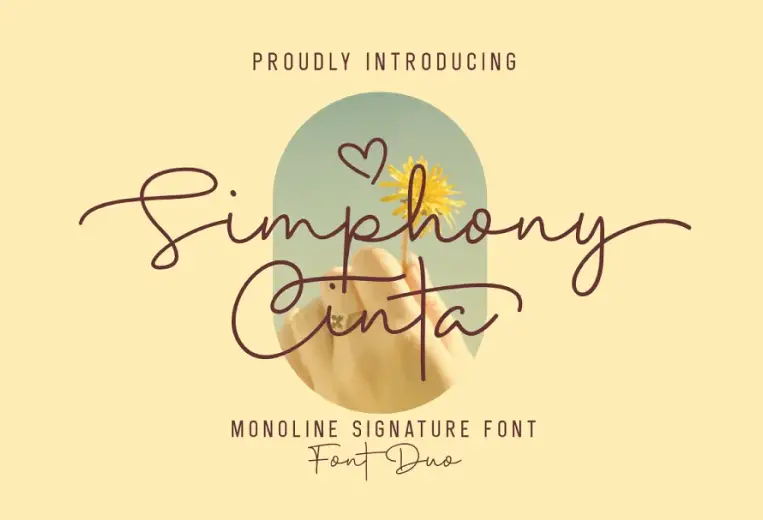
Questo tipo di carattere viene fornito con alternanze e legature che eleveranno i tuoi disegni, rendendoli ancora più sofisticati. Inoltre, Simphony Cinta supporta più lingue, il che lo rende ideale per progetti internazionali.
Cristina Firma
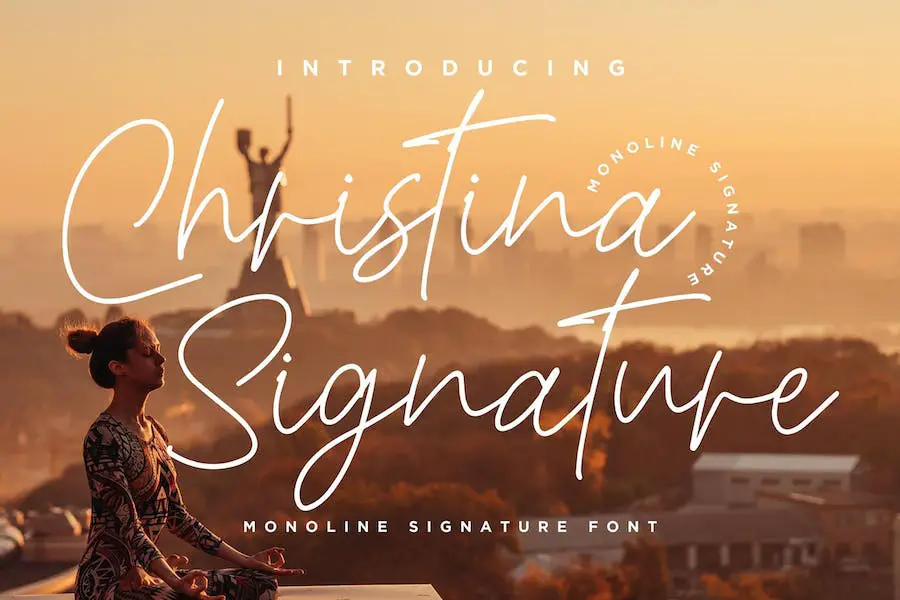
Se stai cercando caratteri di firma Google o caratteri di firma Adobe, Christina Signature è un'ottima opzione. È adatto anche per caratteri distintivi per Word, Canva, Circuit, Figma, disegni di tatuaggi e fotografie. Puoi persino usarlo per le firme e-mail per aggiungere un tocco personale alle tue e-mail.
Questo carattere corsivo ha uno stile calligrafico che lo distingue dagli altri caratteri. Le curve e gli anelli delle lettere danno un senso di eleganza e raffinatezza a qualsiasi design. Sia che tu voglia usarlo per scopi personali o di branding, Christina Signature è una scelta eccellente.
Mashiny
Questo font è dotato di caratteristiche impressionanti, come lettere maiuscole e minuscole, legature, numeri, simboli e supporto multilingue. Inoltre, funziona perfettamente sia su PC che su Mac ed è accessibile tramite Adobe Illustrator, Adobe Photoshop, Adobe InDesign e Microsoft Word. I caratteri codificati PUA lo rendono completamente accessibile senza software di progettazione aggiuntivo.
Il design unico di Mashiny offre una vasta gamma di possibilità quando si tratta di creare caratteri distintivi per Google, Adobe, Word, Canva, Circuit, Figma, Tattoo o fotografia. È anche una scelta eccellente per le firme e-mail, i caratteri della firma corsiva, i caratteri calligrafici della firma e i design del marchio.
Firma di Queenstown
Il carattere presenta un set completo di caratteri dalla A alla Z, numeri e punteggiatura in OpenType Standard, accenti in caratteri multilingue e legature. Queenstown Signature supporta anche numerose lingue tra cui afrikaans, albanese, catalano, francese, tedesco, indonesiano, italiano, portoghese, spagnolo, svedese, zulu e altro ancora.
Florissant
Florissant è un font calligrafico eccezionale progettato per aggiungere un tocco di modernità e stile ai tuoi progetti. Con il suo fascino unico, questo font è perfetto per creare loghi, inviti, articoli di cancelleria, progetti di matrimoni, post sui social media, pubblicità, confezioni di prodotti, etichette, fotografie, filigrane, eventi speciali o qualsiasi altra cosa che richieda un tocco di eleganza.
Questo carattere distintivo viene fornito con lettere maiuscole e minuscole, numeri e punteggiatura. Dispone inoltre di supporto multilingue e design delle legature, che lo rendono adatto a vari scopi in diverse lingue. Inoltre, Florissant è codificato PUA, il che significa che è facilmente accessibile tramite Mappa caratteri su Windows e Font Book su Mac.
Il dottore
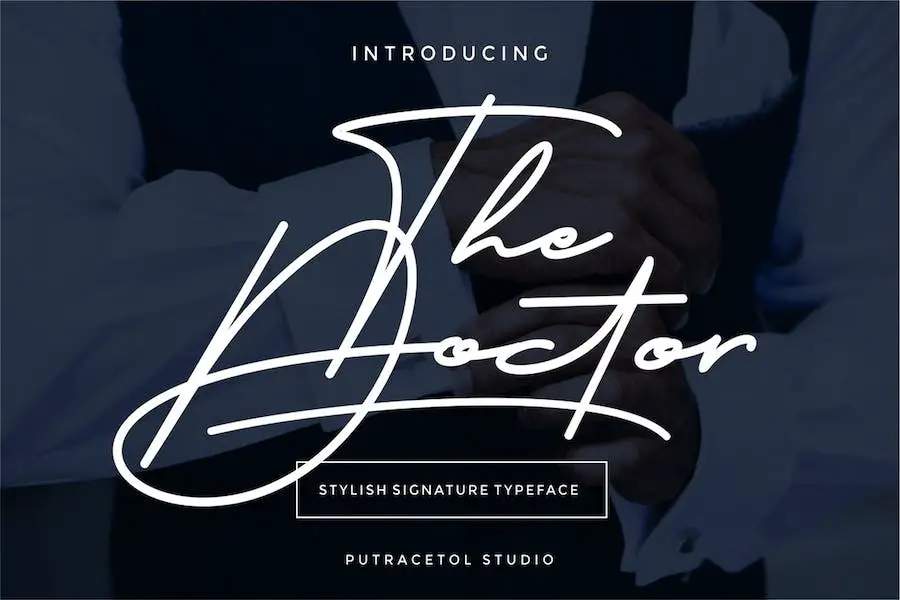
The Doctor è un elegante carattere distintivo che presenta un flusso naturale, di classe ed elegante. Questo carattere di scrittura a mano viene fornito con lettere maiuscole e minuscole, caratteri alternativi, numeri, punteggiatura e simboli. È perfetto per l'uso in vari progetti come branding, loghi, inviti, etichette, citazioni, grafica per social media e molti altri.